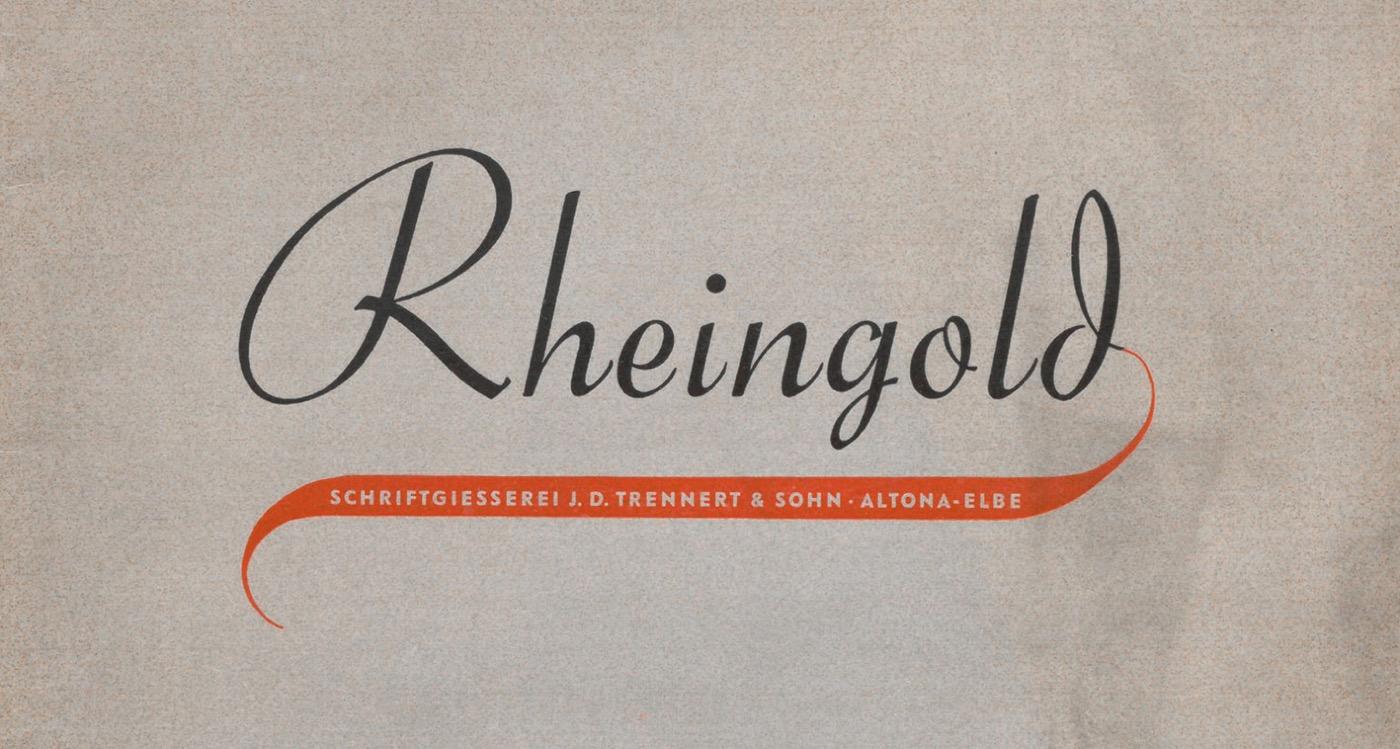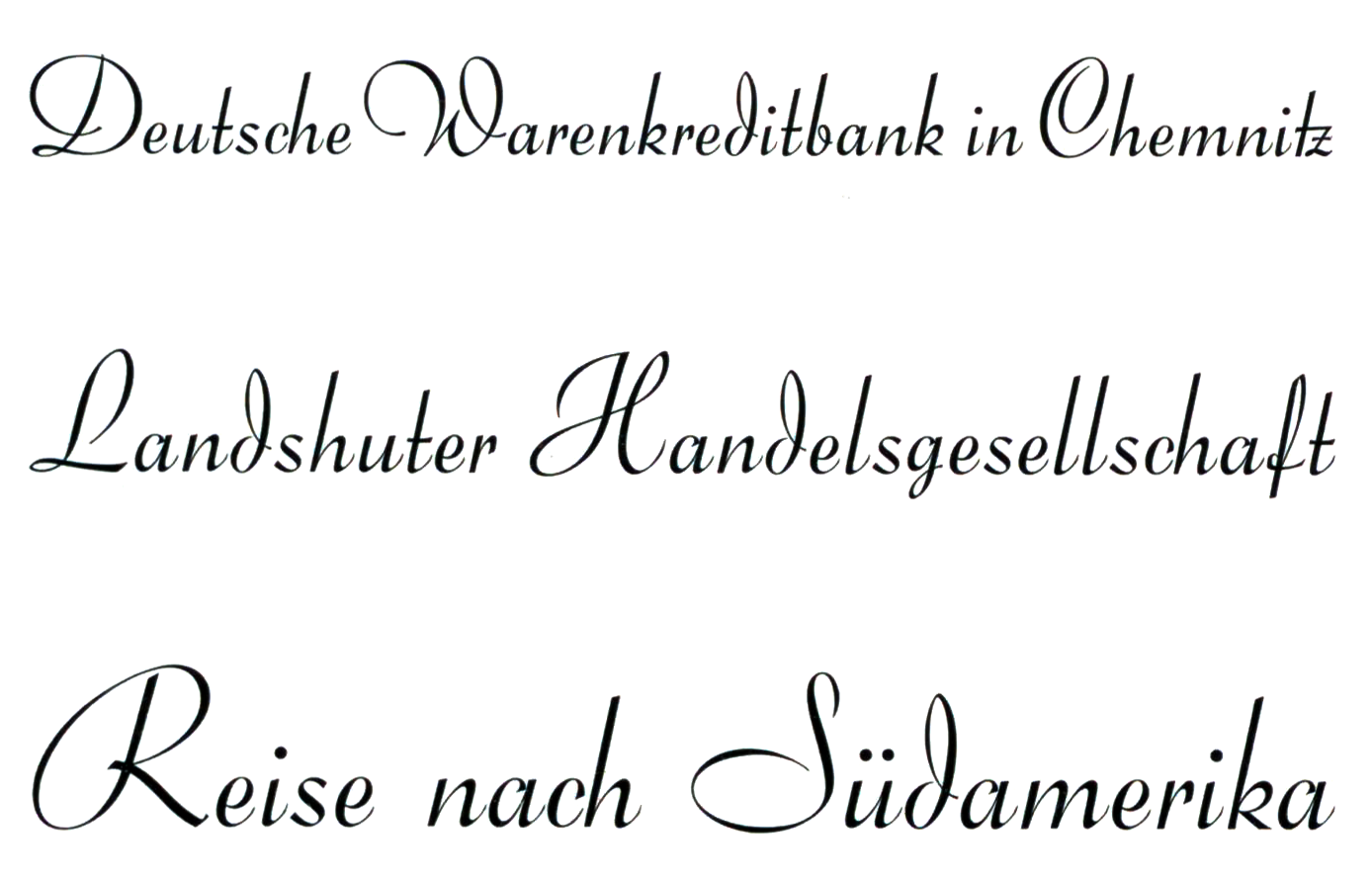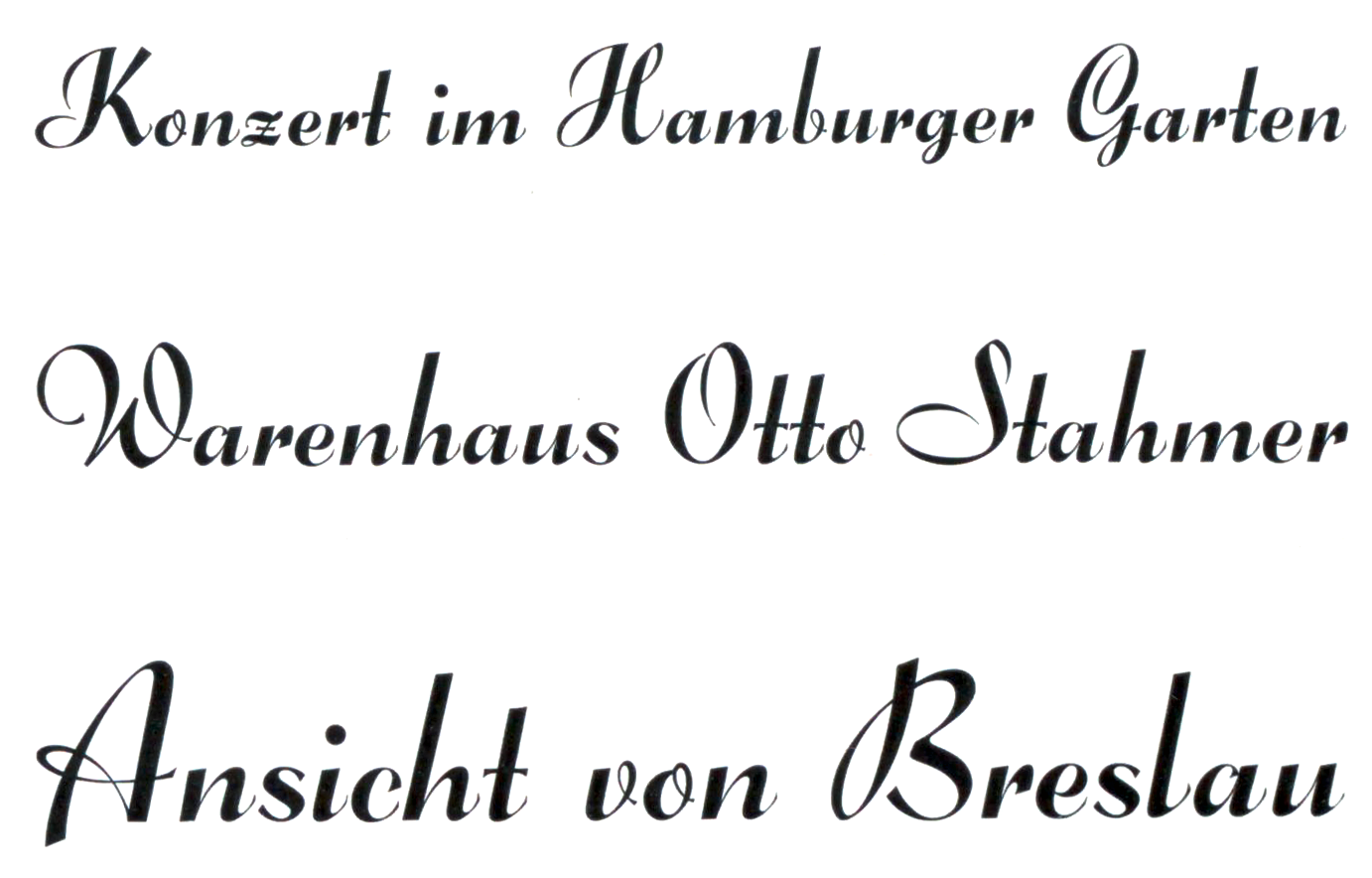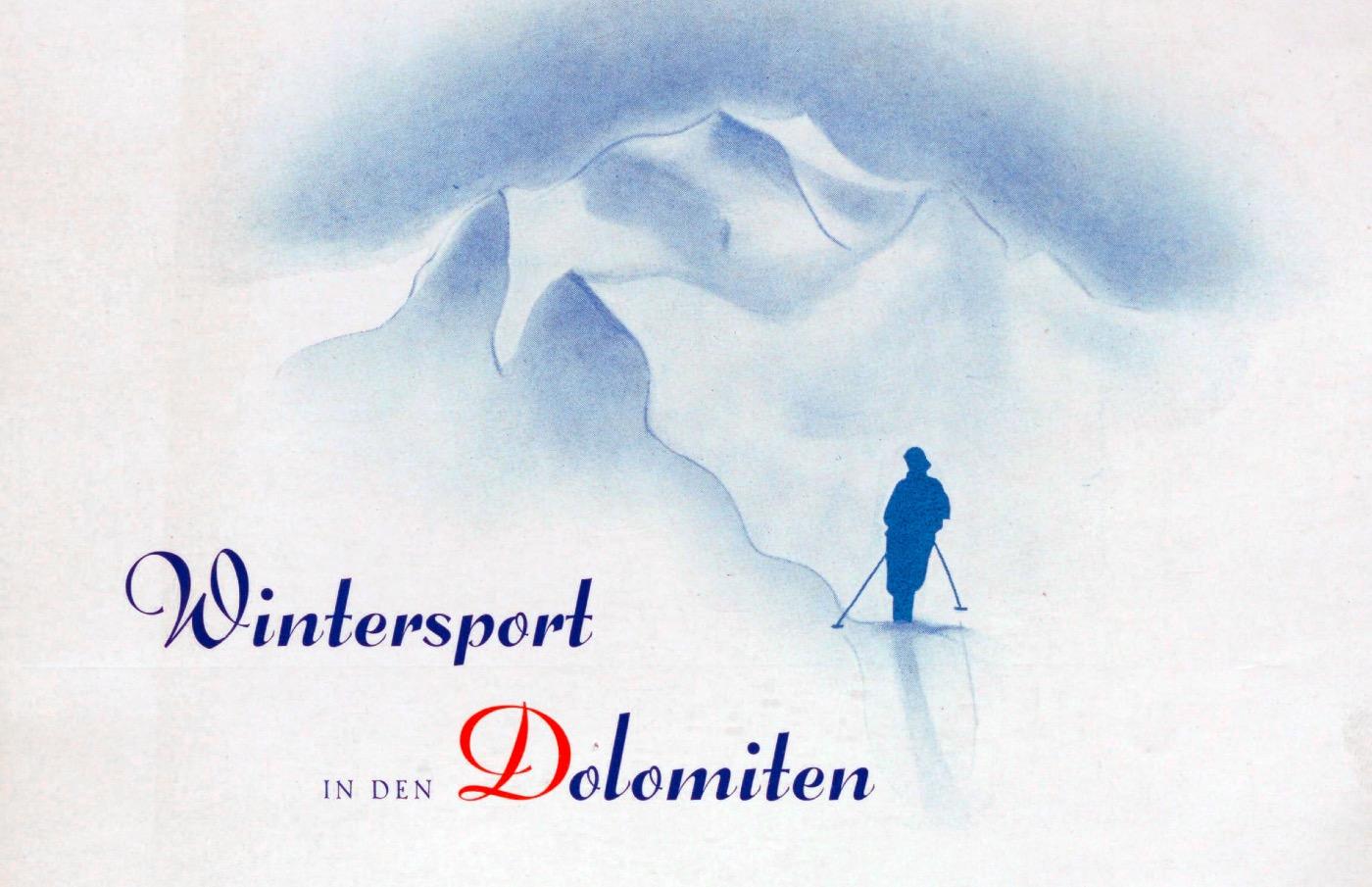
Font-Wiki: Rheingold [Trennert]
Die Rheingold ist eine unverbundene Schreibschrift von Erich Mollowitz aus den 1930er-Jahren. Die Schrift in zwei Strichstärken erschien in Partnerschaft als Rheingold bei Trennert in Hamburg. Bekannter ist der Entwurf unter dem ursprünglich bei C.E. Weber benutzten Namen Forelle. Eine Digitalisierung gibt es unter dem Namen Forelle Pro von RMU Fonts.